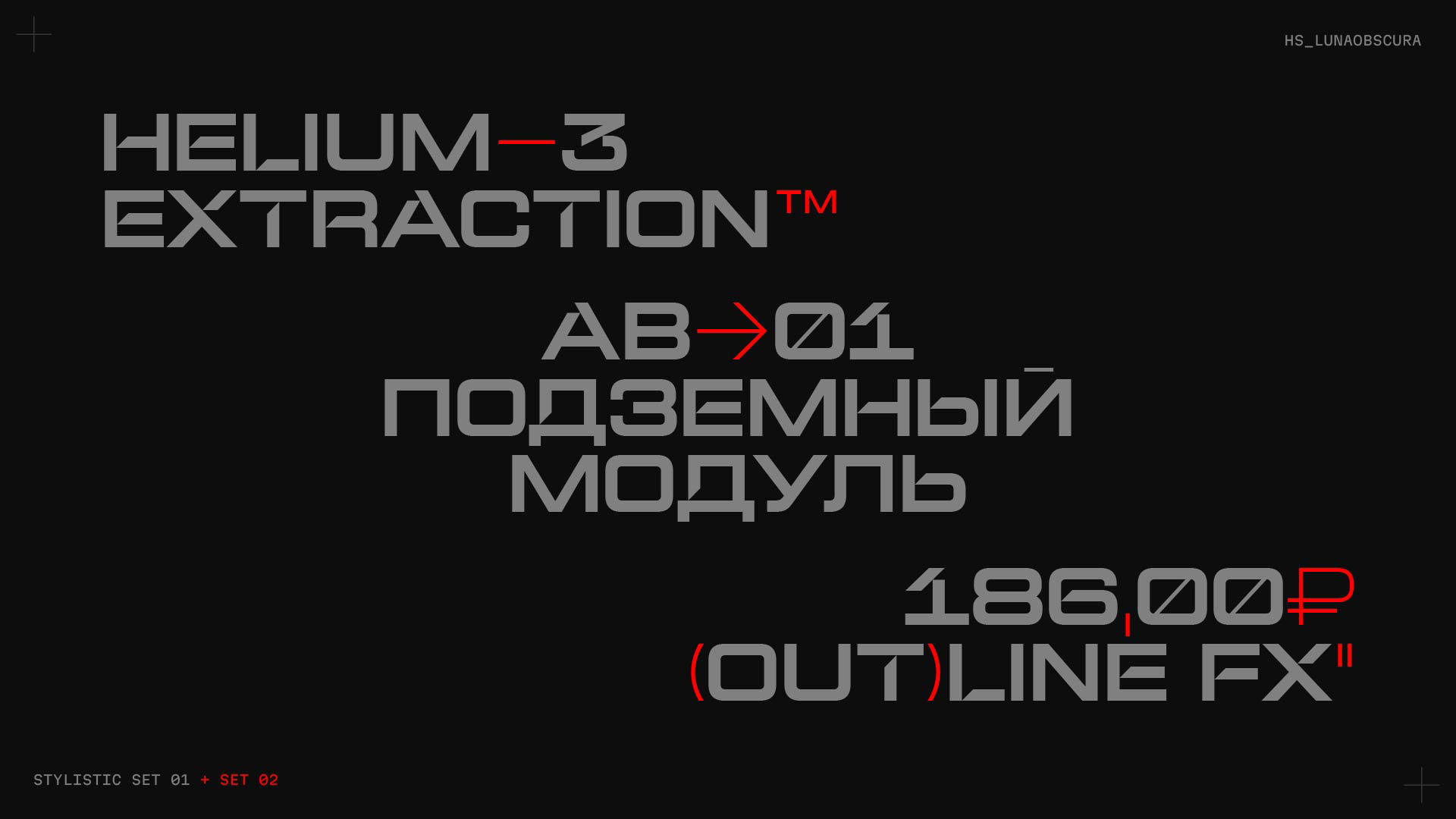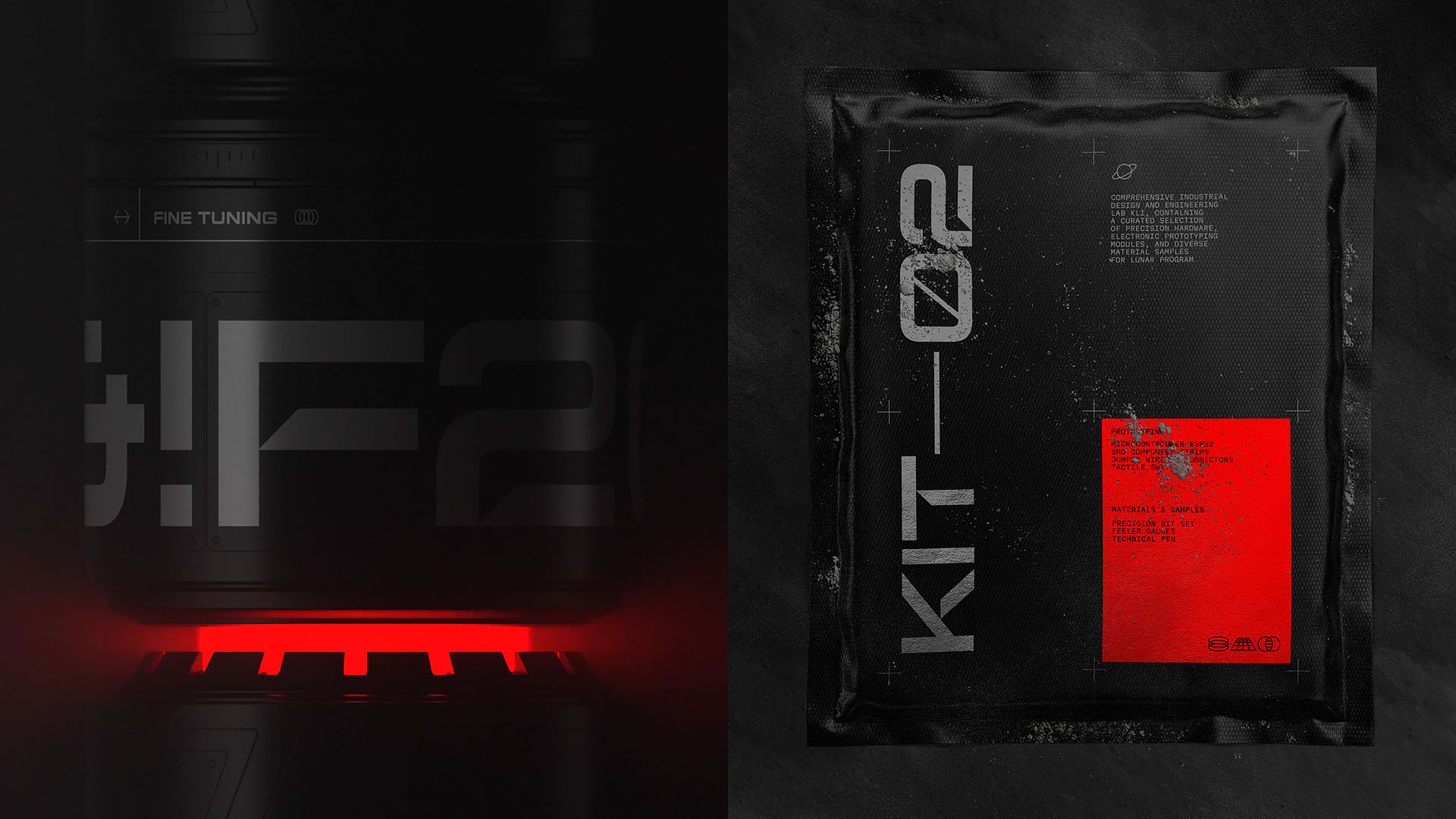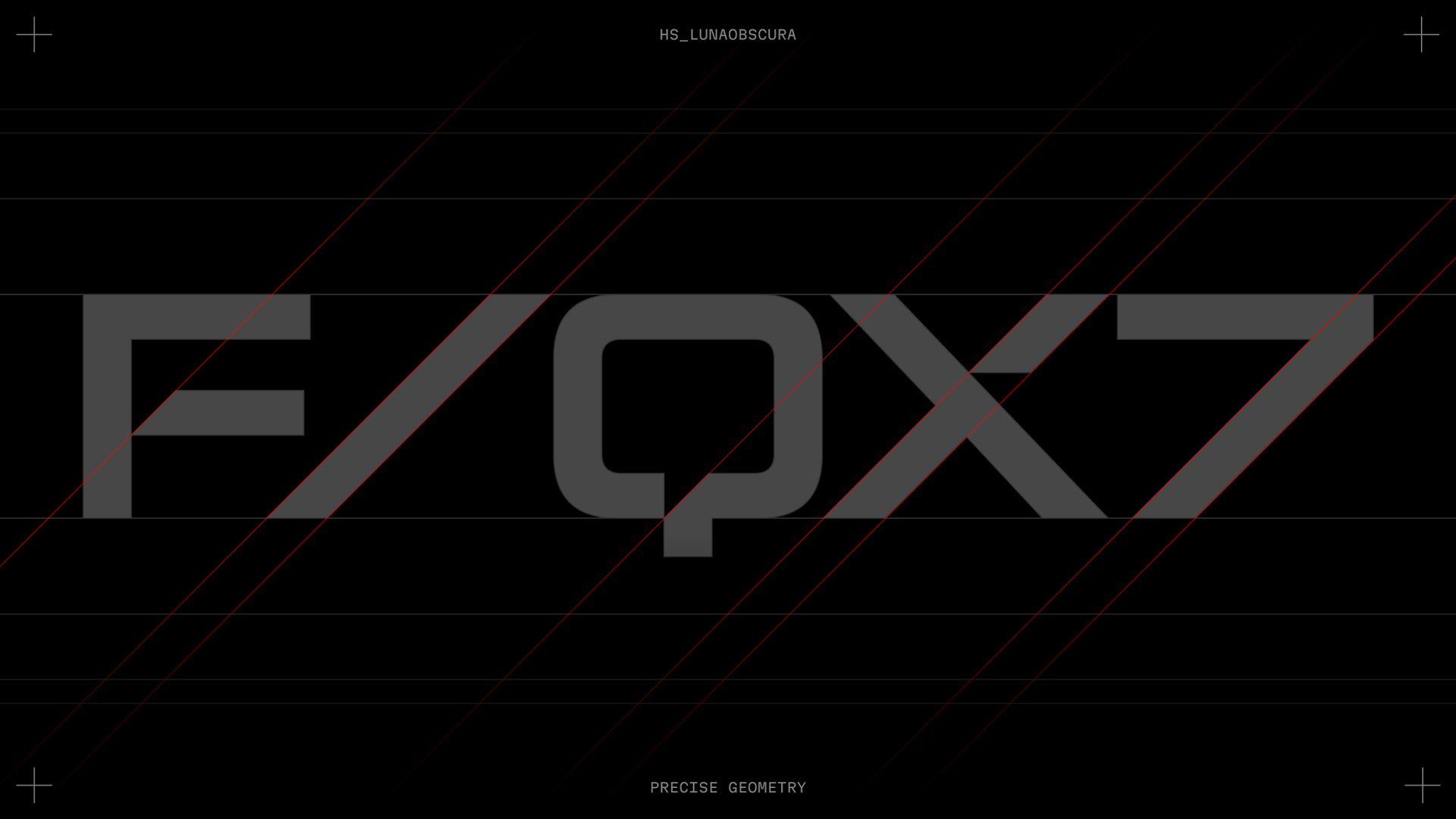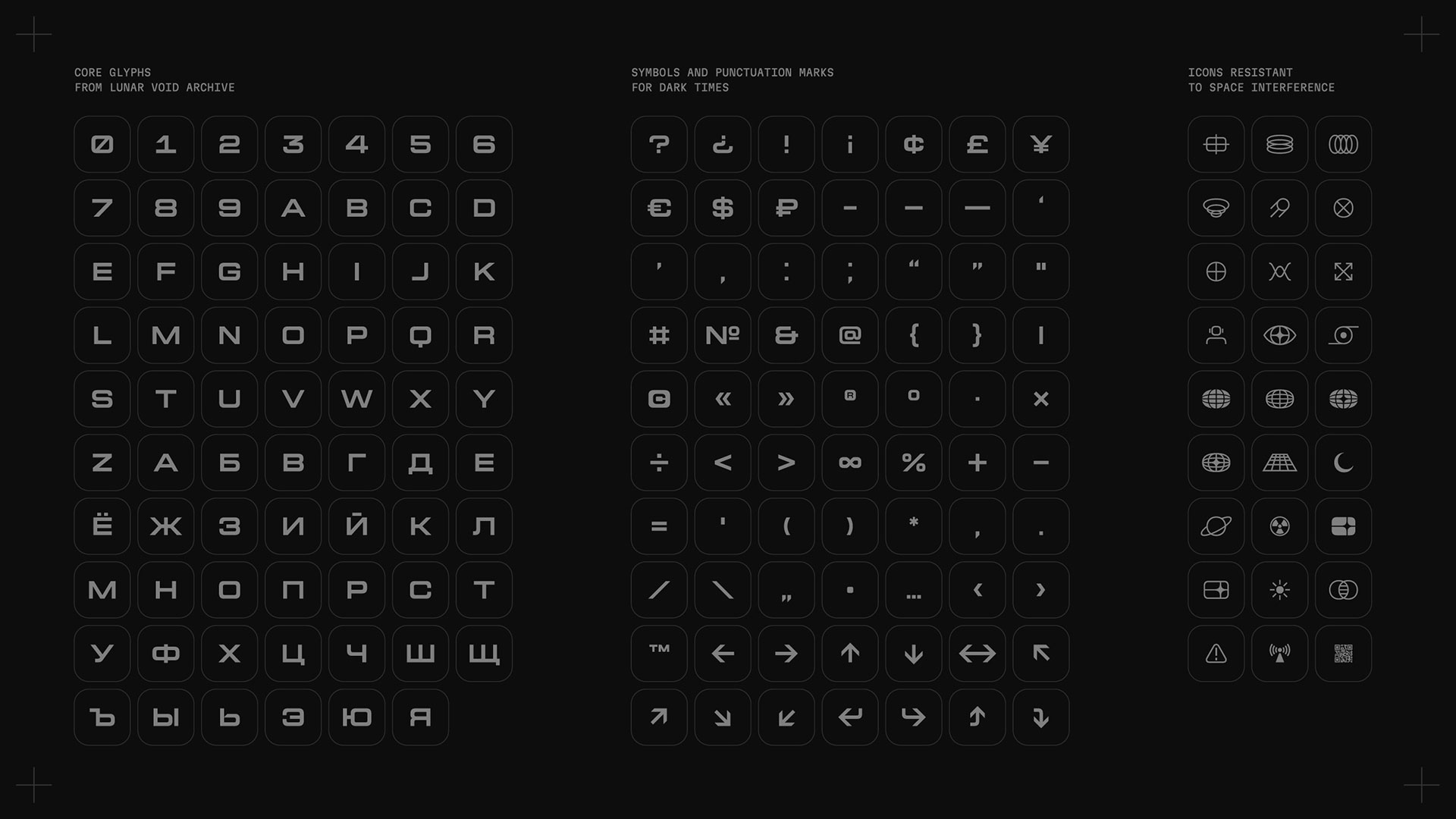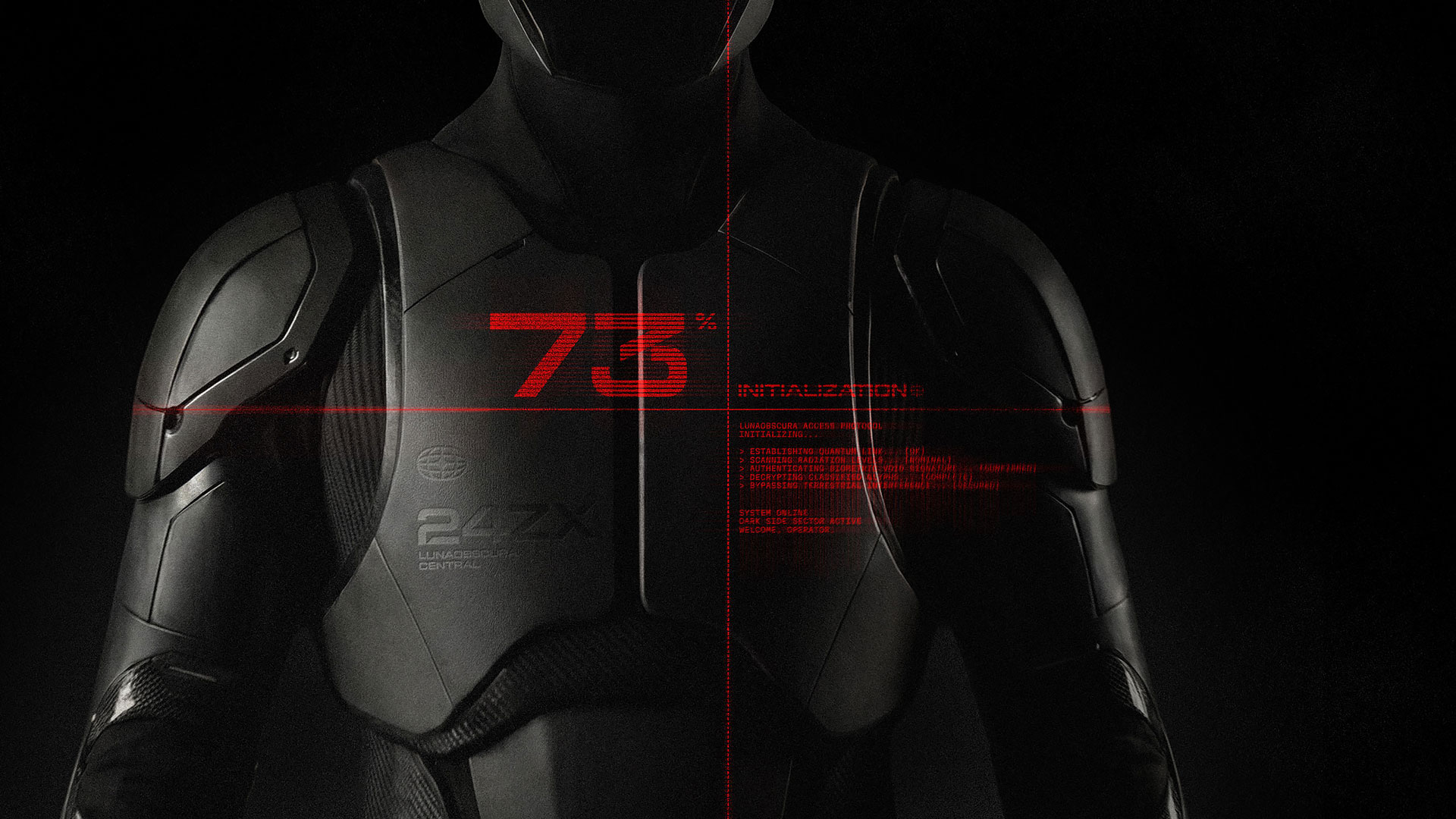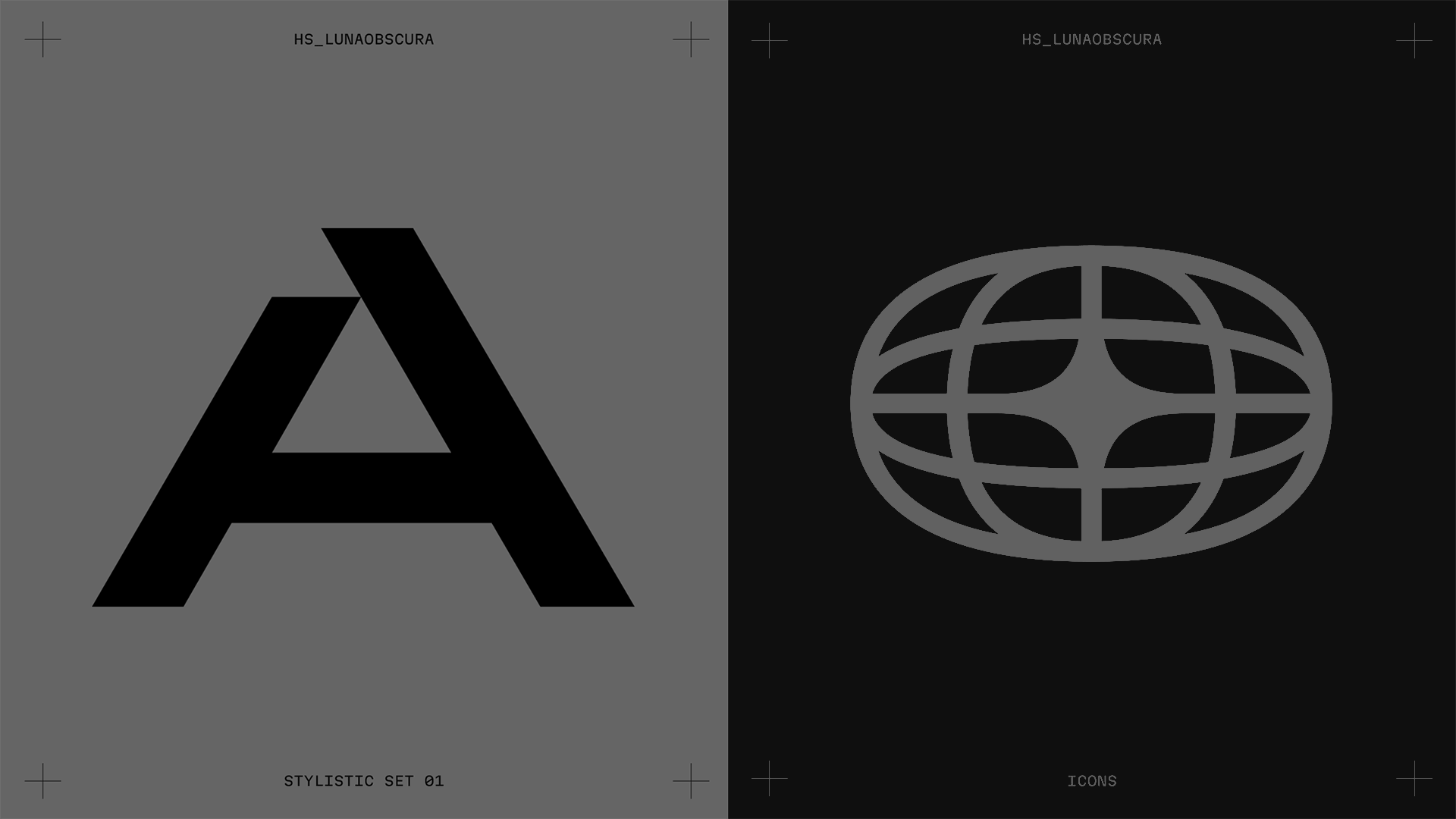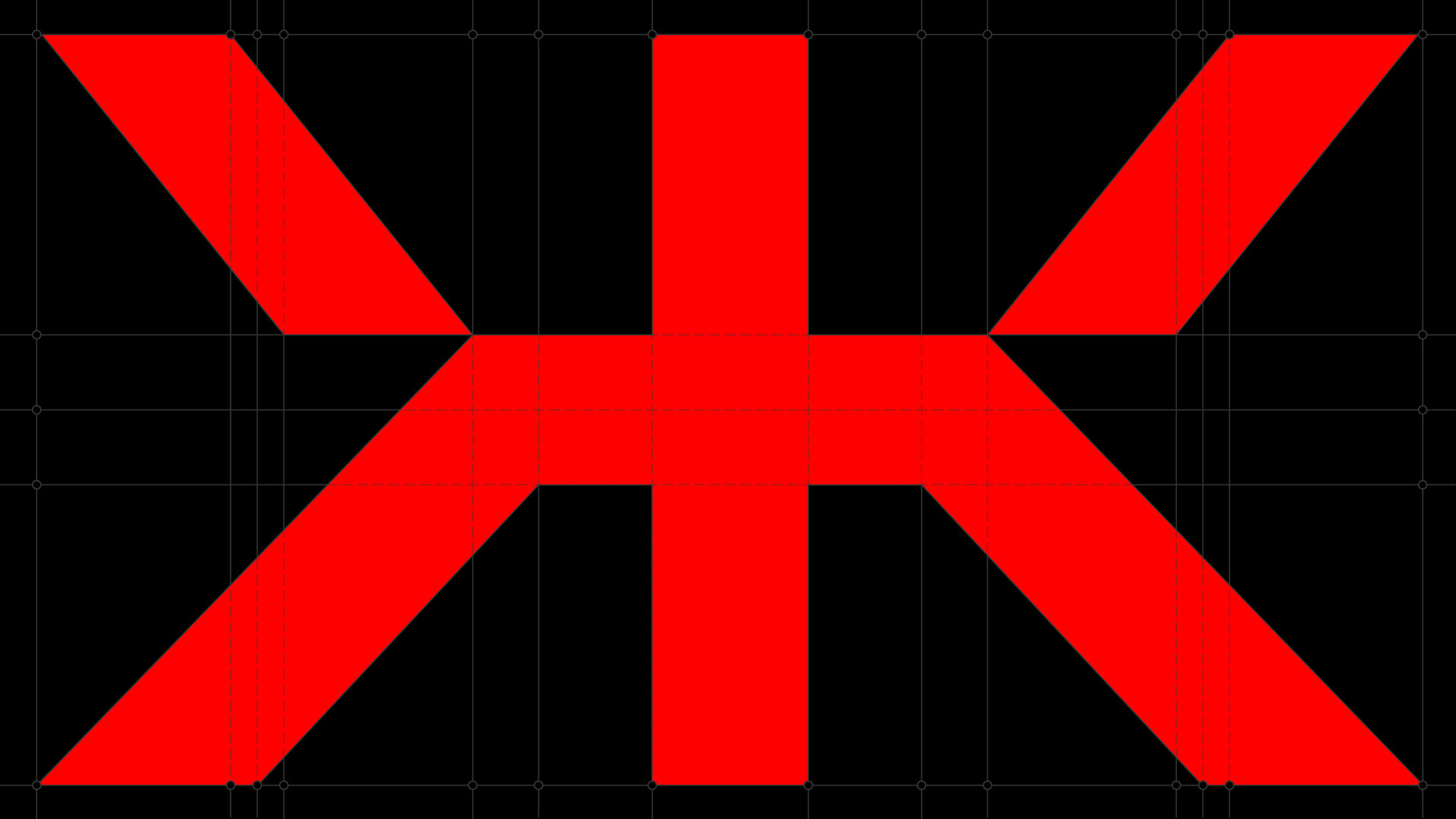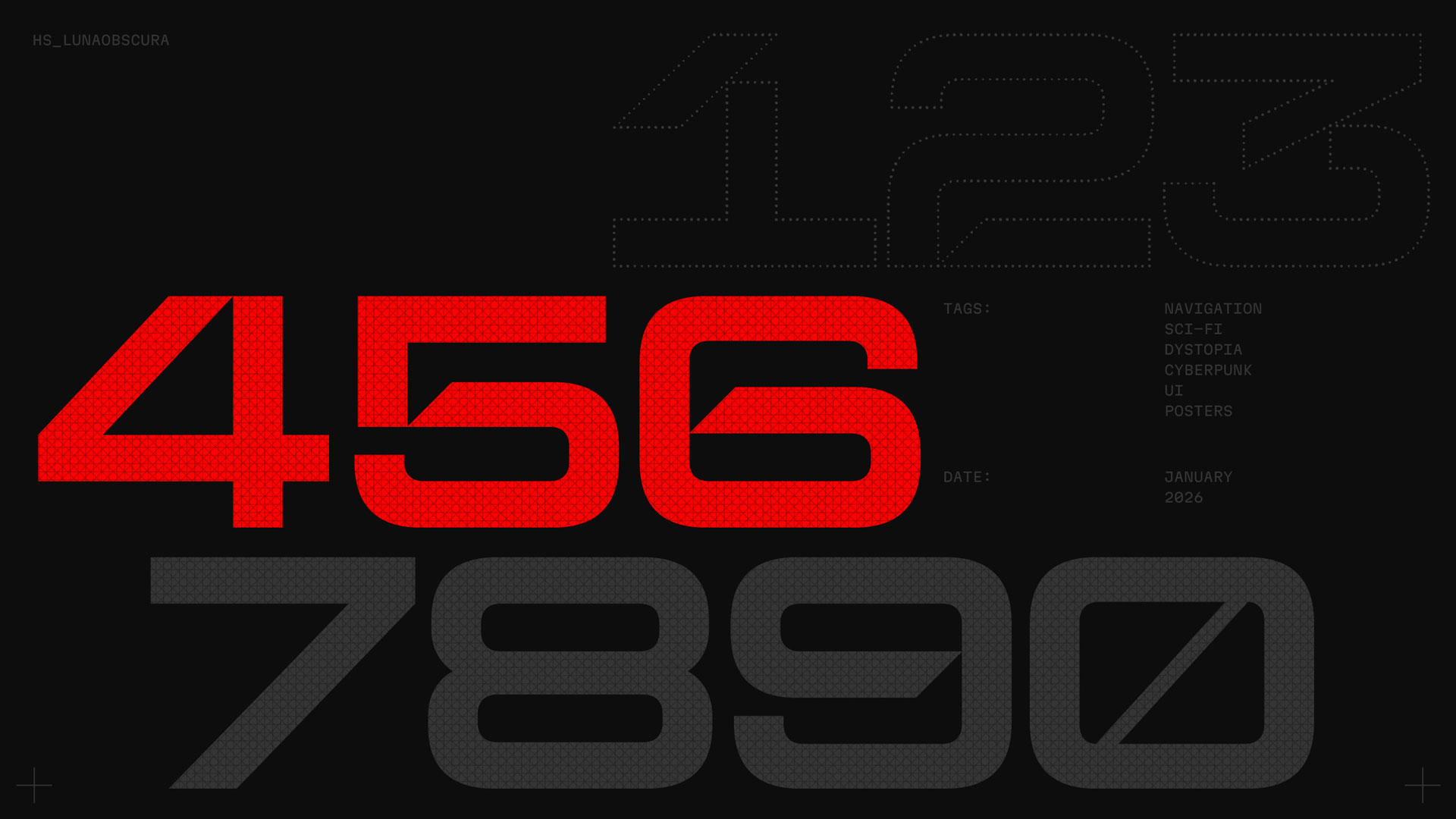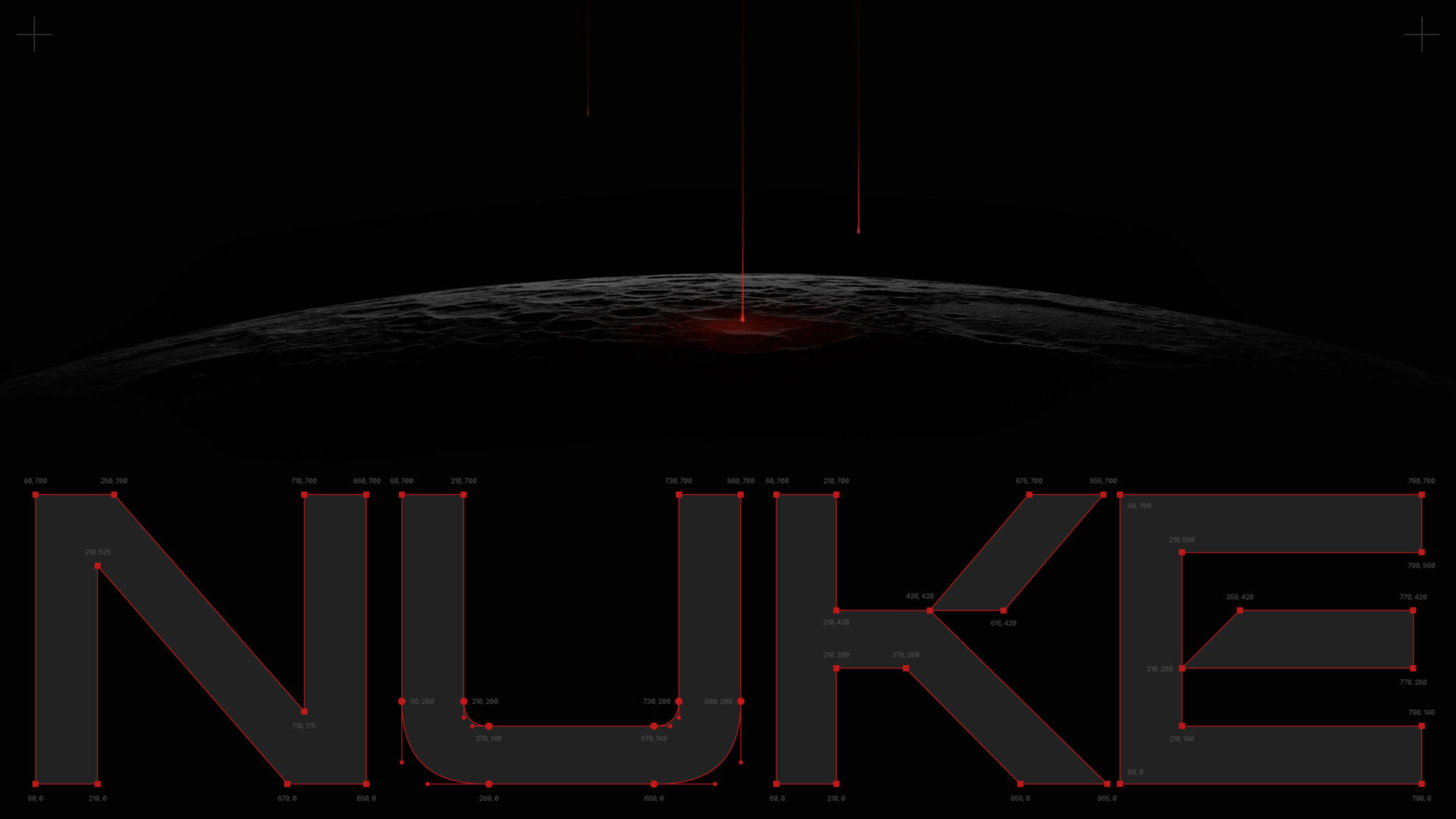
Экспериментальный шрифт
LunaObscura
LunaObscura — супер-акцидентный экспериментальный дисплейный шрифт, созданный как концептуальный артефакт с тёмной стороны Луны для sci-fi проектов, навигации и технологичной айдентики. В знаки зашиты OpenType-фичи с разными типами скосов, которые позволяют динамически менять характер и пластику букв прямо в наборе. Чтобы раскрыть весь потенциал гарнитуры, был разработан промо-сайт, где пользователь может полностью погрузиться в атмосферу проекта, изучить анатомию глифов и в реальном времени испытать шрифт в работе.